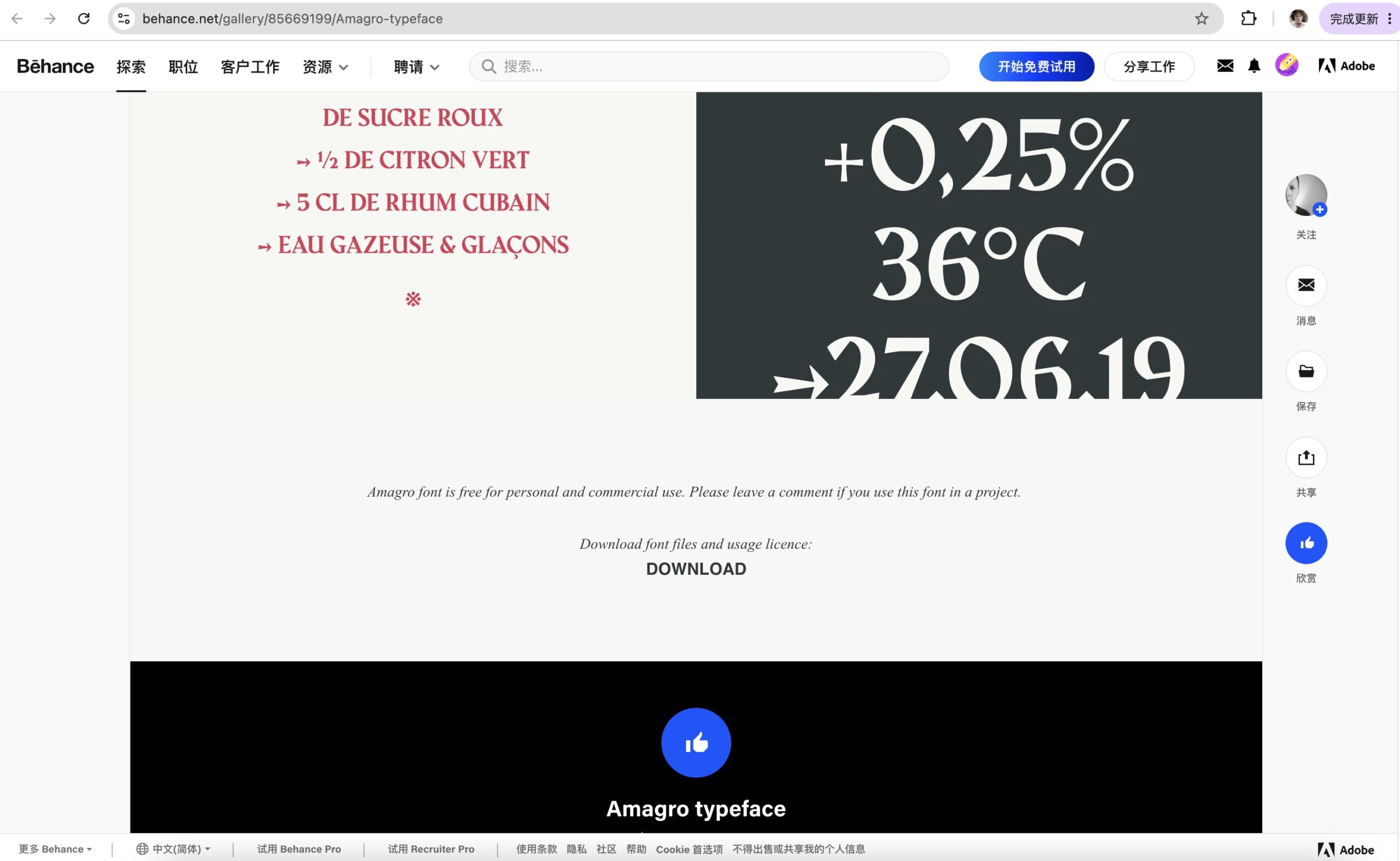
Amagro
Amagro 是一款由设计师 Fabio Servolo 创作的现代衬线字体(Serif Typeface)。字体以简洁、理性的几何结构为基础,同时融入具有装饰性的细节处理,在传统衬线字体的优雅气质与现代视觉设计之间取得平衡。整体设计强调清晰的结构关系与独特的字形特征,使其既适合作为品牌展示字体,也能够满足多种平面设计场景的排版需求。
从整体字形来看,Amagro 采用较为纤细的衬线结构,字母比例经过精心调整,呈现出稳定、克制的视觉效果。与传统古典衬线字体相比,该字体减少了复杂的笔画变化,通过更明确的几何切割和锐利转角增强现代感,使文字在保持优雅气质的同时,也具有更加鲜明的设计辨识度。
在细节处理方面,Amagro 最大的特点体现在字母结构中的几何化设计。部分字母的衬线并非采用传统圆润过渡,而是通过倾斜切角、尖锐边缘以及简洁的连接方式塑造独特轮廓。例如大写字母 A 的顶部结构与底部衬线呈现出明显的几何比例关系,字母 G、R、M 等字符也通过细微的结构变化展现出更加现代的排版风格。
该字体在笔画粗细控制上保持较高的一致性,纤细的线条与开放式字腔形成良好的视觉平衡,使文字在大尺寸展示时具有精致的高级感。同时,较宽松的字面空间也提升了字体在标题排版中的呼吸感,避免了传统高对比衬线字体容易产生的拥挤效果。
从应用场景来看,Amagro 更适合作为展示型字体使用,尤其适用于品牌标识、时尚杂志、产品包装、精品海报、婚礼设计以及高端视觉项目。其简洁但具有辨识度的结构,使字体能够传递现代、精致、理性的品牌气质。
此外,Amagro 包含较完整的拉丁字符支持,并提供数字、标点符号以及多语言扩展字符,能够满足国际化设计项目中的基础排版需求。作为一款免费可商用字体,它为设计师提供了更加灵活的使用空间。
总体来看,Amagro 是一款将几何美学与经典衬线结构结合的现代字体。它没有过度强调装饰效果,而是通过精准的比例控制、独特的切角设计以及简洁的字形关系,创造出兼具高级感与现代感的视觉风格。适合作为品牌设计、包装视觉和高端标题排版中的特色字体使用。